今回は「シネマ風・映画字幕風」にぴったりなフリーフォントをご紹介します。
映画の字幕フォントといえば、シンプルでありながら視認性が高く、観客がストーリーに集中できるよう工夫されています。その中には、手書き文字のような柔らかさを取り入れたものもあり、読みやすさと雰囲気づくりを両立しているのが特長です。さらに、映画字幕では「長体(縦に少し伸びた形)」の文字が採用されることが多く、独特の映画らしい印象を与えてくれます。
今回は、そんなシネマ風・映画字幕風の特徴を持ったフリーフォントをピックアップしました。実際の映画字幕をイメージしたサンプル画像とあわせて掲載しているので、ぜひ参考にしてみてください。
「シネマ風・映画字幕風」のフリーフォント
最近では一般的なゴシック体のような読みやすいフォントに置き換わってしまった映画字幕が多いですが、少し前はこの手書きのような雰囲気がある映画字幕風フォントが主流でした。以下のサンプルは、本記事の一部のフォントですが、このようなスタイルのフォントをご紹介します。
てあとりずむ
「てあとりずむ」フォントは、優しい印象も持っている映画字幕フォントです。
映画字幕フォントとして、一番ベージックなタイプかと思います。
しねきゃぷしょん
「しねきゃぷしょん」フォントは、フォント名の通り映画字幕のために制作されたフォントなので、シネマ風の印象が出るフォントです。
てあとる16
「てあとる16」フォントは、手書き文字とゴシック体の間のようなフォントです。そのため、クセも少ないフォントとなっているので、可読性が高く映像の字幕にぴったりなフォントです。
エビハラのくせ字
「エビハラのくせ字」フォントは、手書き感とクセが少し強めのフォントですが、映像にちょっとしたアクセントを足したいときにぴったりなフォントです。
かんじゅくゴシック
「かんじゅくゴシック」フォントは、ゴシック体フォントですが、文字の輪郭にガタガタしている加工が施されていることで、レトロな味わいや温度感を感じるフォントとなっています。
新レトロ丸ゴシック
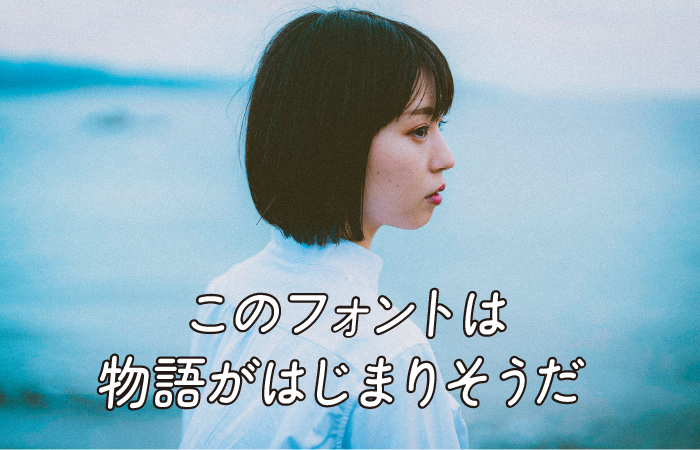
新レトロ丸ゴシックは、写植時代に使われていた丸ゴシックを参考に作られたどこか懐かしい表情のあるフォントです。レトロな風合いが字幕文字にもぴったりです。
ZEN丸ゴシック
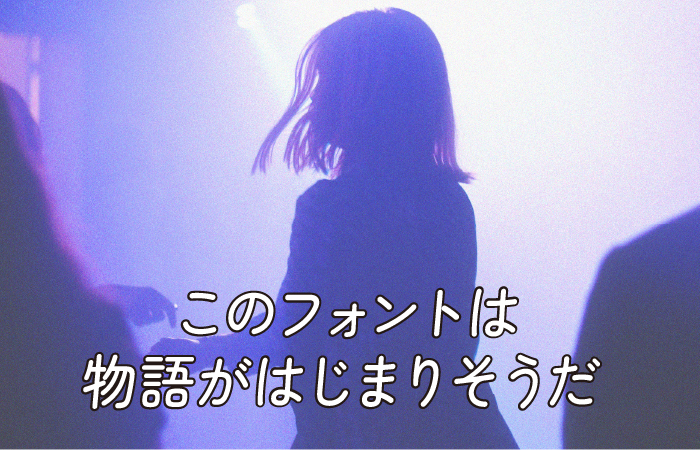
ZEN丸ゴシックフォントは、ナチュラルな印象でこぶりなかな文字が特徴的な丸ゴシック体のフォントです。
全体的に、縦に長い長体スタイルとなっているので、長文で文字を組んだ際でもしっかりとした印象になるので、字幕にもぴったりです。
スマートフォントUI
「スマートフォントUI」フォントは、長体なゴシック体フォントです。ゴシック体なので、字幕文字として可読性も高いデザインなので、字幕フォントとしておすすめの1つです。